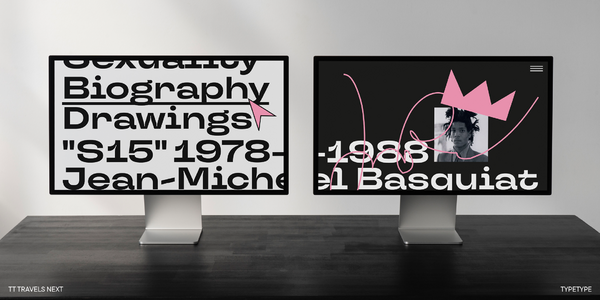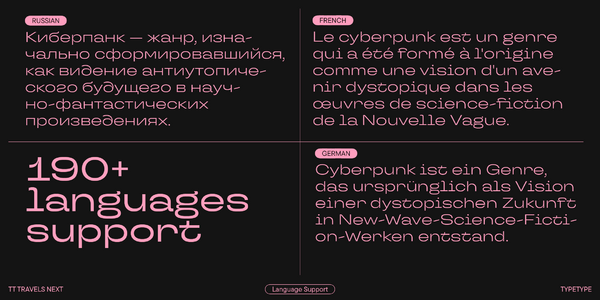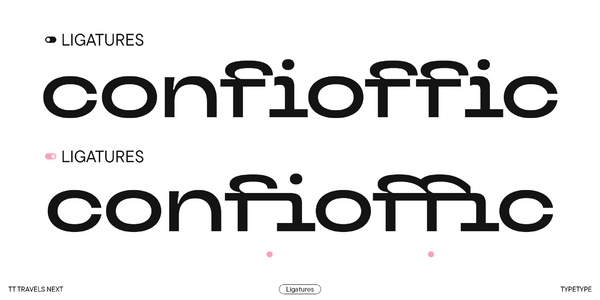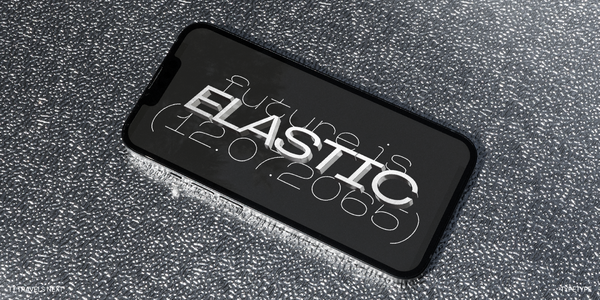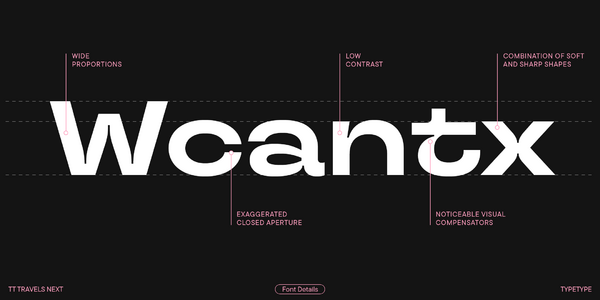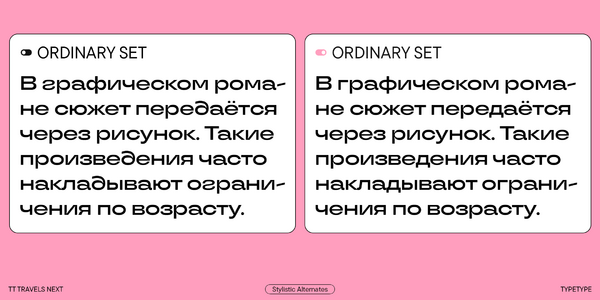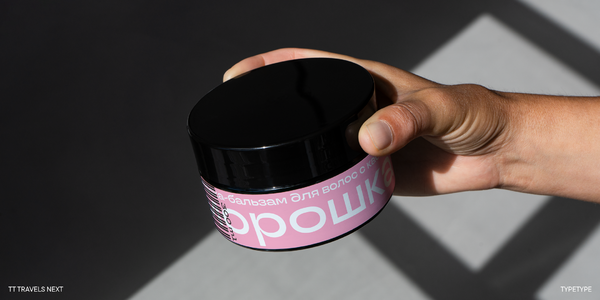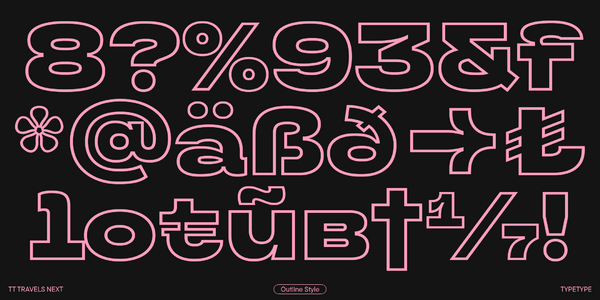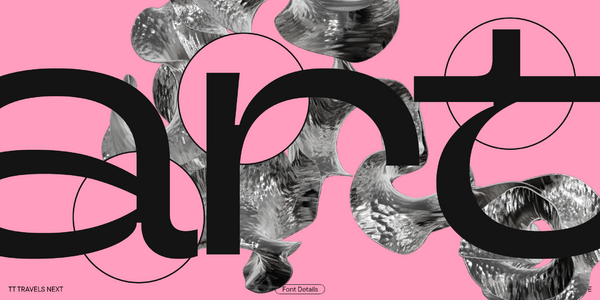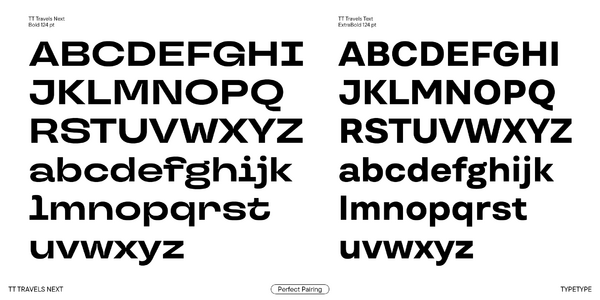
TT Travels Next — ТТ Травелс Некст
Произносится «ТТ Травелс Некст». «Travels» — производное слово от travel, в переводе с английского «путешествие», «Next» — в переводе с английского «следующий». Буквы «TT» являются аббревиатурой названия компании.
TT Travels Next — сверхмодный широкий гротеск с дерзким характером. Это акцидентный шрифт, в котором одновременно уживаются плавные и резкие формы.
Сверхмодный и современный широкий акцидентный гротеск
Идея создания альтернативной версии гарнитуры TT Travels родилась на конференции мэйл/дрибл, которая проходила в августе 2020 года в Москве. Весь брендинг конференции был выполнен с использованием гарнитуры TT Travels, и при всей красоте вёрстки нам показалось, что если бы шрифт был более акцидентным и радикальным, он бы ещё лучше дополнил графику мероприятия.
Кроме того, в гарнитуре TT Travels Next есть два классных аутлайн начертаний
В наклонных начертаниях мы специально увеличили угол наклона до 14 градусов
TT Travels Next в дизайне
О гарнитуре TT Travels Next
Поддержка языков 200+
Встречайте TT Travels Next — экспериментальную акцидентную гарнитуру, созданную на основе оригинального TT Travels!
Создавая TT Travels Next, мы хотели ответить себе на вопрос, каким бы стал оригинальный TT Travels, если бы превратился в дерзкого и прямолинейного «панка», отбросив свой конформизм и компромиссность. Так, мы наделили новую гарнитуру радикальным характером и выдвинули акцидентные детали на первый план.
TT Travels Next — сверхмодный широкий гротеск. Широкие пропорции — одна из отличительных черт этой гарнитуры: знаки почти не сужаются при переходе от толстого начертания к тонкому. Кроме того, шрифт отличает сверхзакрытая апертура, небольшой контраст и заметные визуальные компенсаторы. Интересно, что в TT Travels Next одновременно уживаются плавные и резкие формы, что делает его разносторонним, необычным и притягательным. А в начертаниях Italic мы намеренно увеличили угол наклона до 14 градусов, чтобы вы могли набирать резкие динамичные надписи.
Этот стильный и ультрасовременный шрифт идеально подходит для работы с разной версткой — как в печати, так и в вебе. В гарнитуре есть два аутлайн начертания, которые прекрасно сочетаются с прямыми начертаниями и дополняют их, а также отлично работают как акцентные шрифты. А для того, чтобы дизайнеры могли подстраивать TT Travels Next под свои потребности и задачи, в нем есть вариативный шрифт, способный меняться по двум осям — толщине и наклону.
TT Travels Next — это:
• 21 начертание: 9 прямых, и 9 наклонных, два аутлайн начертания и 1 вариативный шрифт;
• 757 знаков в каждом начертании;
• 26 OpenType фич, в том числе стилистические альтернативы, лигатуры, стрелки и цифры в кружочках;
• Поддержка более 190 языков.
Basic Latin Basic Cyrillic Extended Latin Stylistic Alternates, Standard and Discretionary Ligatures|salt,liga,dlig Lining Figures, Currencies Old-style Figures|onum Punctuation, Symbols, Mathematical Symbols, Arrows Stylistic Set 1 (Cyrillic and Latin) |ss01 Figures in circles
ss01 | Ordinary Set
Qg
ss06 | White Circled Figures
13
frac | Fractions
3/4
liga | Standard Ligatures
ffi
onum | Oldstyle Figures
1703
case | Case Sensitive Forms
({[H]})